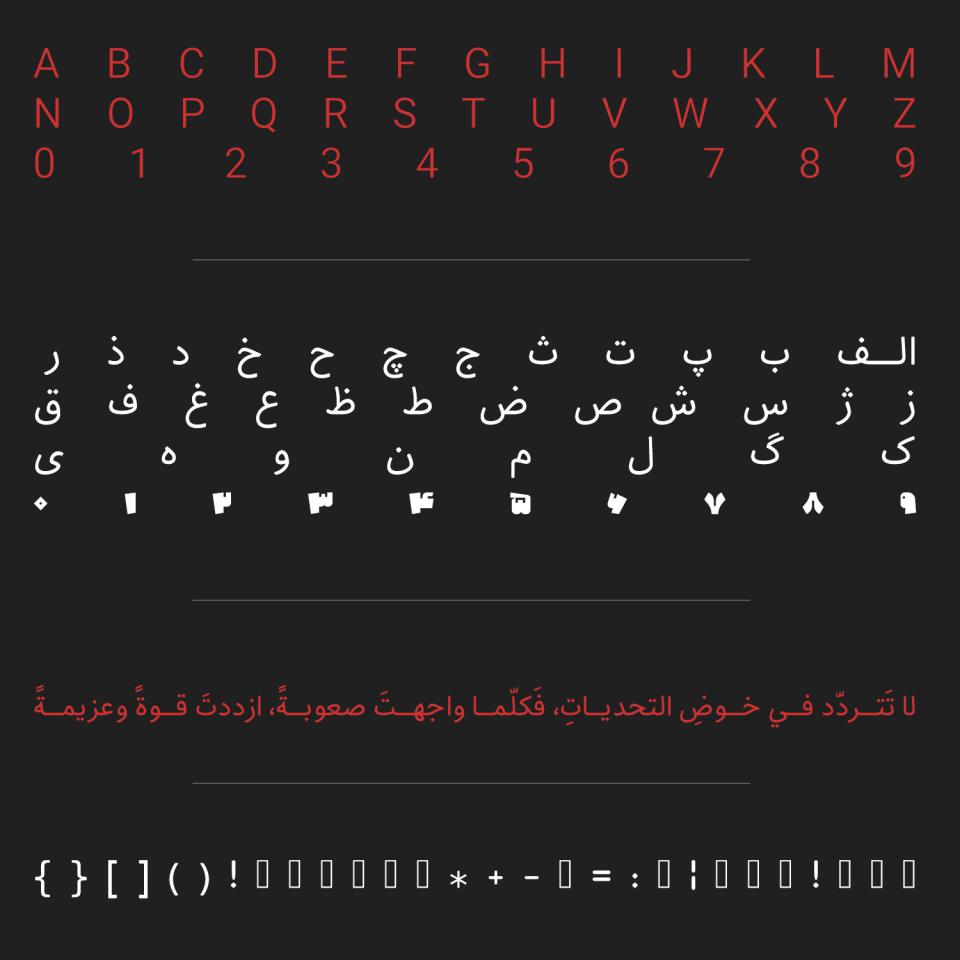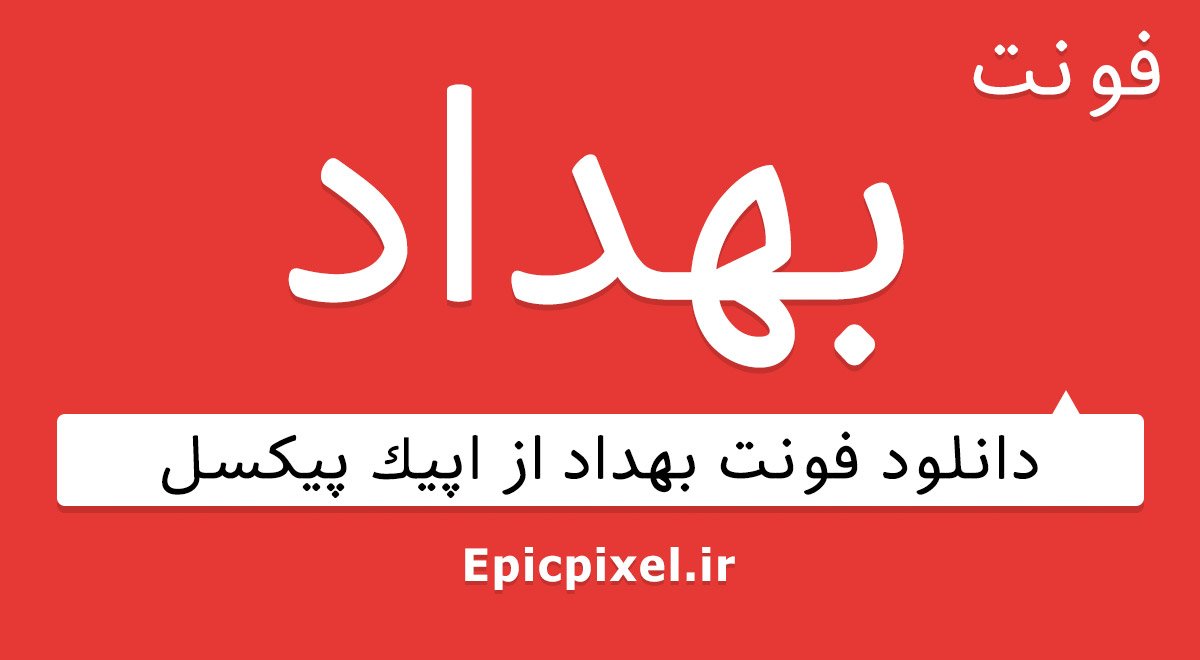
فونت بهداد فارسی Behdad
قلم بهداد یک فونت رایگان با پشتیبانی کامل از زبان های فارسی و عربی است که به طور ویژه برای استفاده در نوشته های بلند و متون طولانی طراحی شده است. این تایپ فیس با داشتن سبکی دوستانه و خوانا، تجربه ای راحت برای مطالعه فراهم می آورد و برای طیف وسیعی از کاربردها از جمله چاپ، رسانه های دیجیتال و نرم افزارها مناسب است. طراحی خاص آن با منحنی های نرم و دندانه های مورب، ظاهری جذاب به آن بخشیده که آن را از سایر قلم ها متمایز می کند.
معرفی قلم بهداد برای متون بلند فارسی و عربی
قلم بهداد یک قلم آزاد و رایگان است که به طور کامل از دو زبان فارسی و عربی پشتیبانی می کند. این تایپ فیس به خصوص برای نگارش و نمایش متون طولانی و پیوسته بسیار مناسب است و به دلیل خوانایی بالای خود، چشم خواننده را خسته نمی کند.
طراحی این قلم ارزشمند توسط محمد صالح سوزنچی انجام شده است. نام “بهداد” از علاقه یک کودک زنجانی به خط فارسی الهام گرفته شده و روی این فونت قرار داده شده است.
بهداد تنها در یک وزن معمولی (Regular) ارائه می شود که همین وزن برای کاربرد اصلی آن یعنی استفاده در بدنه متن و نوشته های بلند کافی است. این قلم در زبان فارسی اعداد را به صورت کاملاً فارسی نمایش می دهد و در زبان عربی نیز از اعداد استاندارد آن زبان بهره می برد.
یکی از ویژگی های بصری این قلم، سبک سنس آن است که با ترکیب منحنی های دایره ای و بیضی شکل، ظاهری گرم و دوستانه پیدا کرده است. دندانه ها در برخی حروف به صورت مورب طراحی شده اند تا جلوه ای بصری به تایپ فیس ببخشند و چشمی ها (فضای بسته درون حروف) در حروفی مانند «م» و «ه» کوچک و به شکل سه گوش هستند.
دانلودکاربردهای این قلم بسیار متنوع است. از آن می توان در صنعت نشر، مکاتبات غیررسمی، و به ویژه در زمینه چاپ کتاب و نشریات برای مخاطبان جوان و کودک بهره برد. ظاهر جذاب و خوانای آن، آن را برای استفاده در روزنامه ها و مجلات نیز مناسب می سازد.
نکته مهم این است که بهداد فاقد حروف لاتین است و تنها برای زبان های فارسی و عربی طراحی شده است. بنابراین، اگر نیاز به استفاده از متون لاتین در کنار فارسی یا عربی دارید، باید از یک فونت مکمل برای بخش های انگلیسی استفاده کنید.
کاربردهای قلم بهداد در طراحی و رسانه های دیجیتال
نرم افزارهای گرافیکی و دیجیتال
قلم بهداد یک انتخاب مطلوب برای طراحان گرافیک و توسعه دهندگان وب است. از این فونت می توان در نرم افزارهای دسکتاپ مانند Adobe Photoshop، Adobe Illustrator، Adobe InDesign یا CorelDRAW برای طراحی انواع اقلام چاپی مثل کتاب، مجله، بروشور و پوستر استفاده کرد. همچنین در محیط های دیجیتال، این تایپ فیس در نرم افزارهای موبایل همچون Picsart یا Canva برای طراحی پست های شبکه های اجتماعی، استوری ها و بنرها کاربرد دارد. ظاهر دلنشین و خوانایی بالای بهداد آن را برای استفاده در رابط کاربری (UI) اپلیکیشن های موبایل و صفحات وب سایت ها که حاوی متون بلند هستند، ایده آل می سازد. t,kj finhn